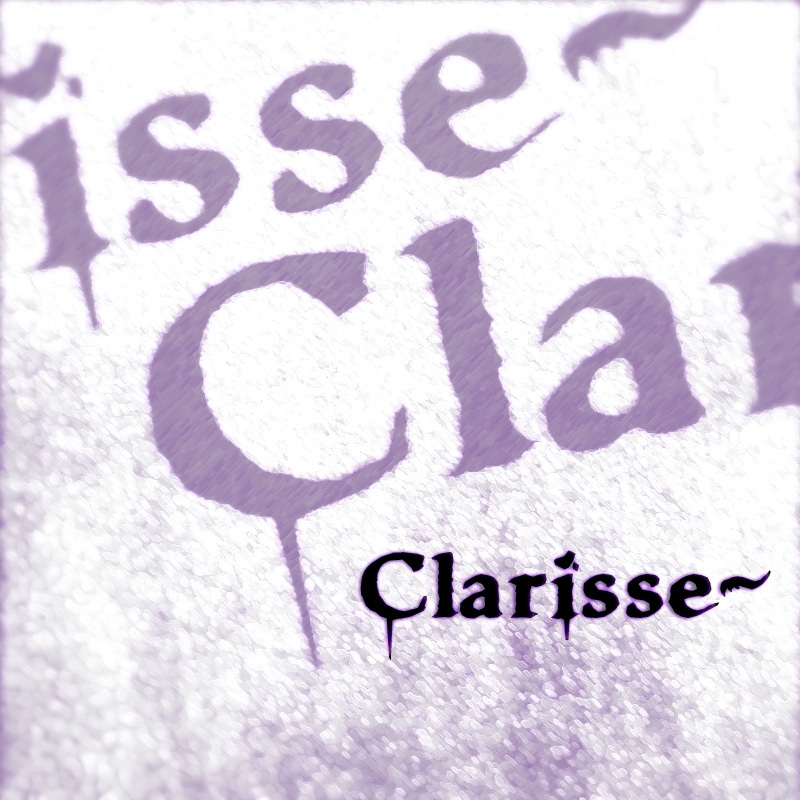
Clarisse to bezpłatny, „zniszczony” krój displayowy o groźnym charakterze, z surowym, gotyckim klimatem, który przywodzi na myśl rzeczy ciosane, wyszczerbione i lekko średniowieczne. Litery opierają się na poszarpanych krawędziach, tępych, klinowatych szeryfach i punktach przypominających ściekający tusz, co nadaje całemu krojowi ton mrocznej baśni, a nie powierzchownego horroru.
Doskonale pasuje do nagłówków plakatów, ulotek wydarzeń z dreszczykiem, logotypów gier, okładek mrocznych książek i opakowań sezonowych, gdzie odrobina grozy pomaga zbudować klimat. Jako darmowy krój, Clarisse najlepiej sprawdza się w krótkich formach, takich jak nagłówki, tytuły czy monogramy, ponieważ to właśnie te poszarpane, „cieknące” detale robią największe wrażenie.